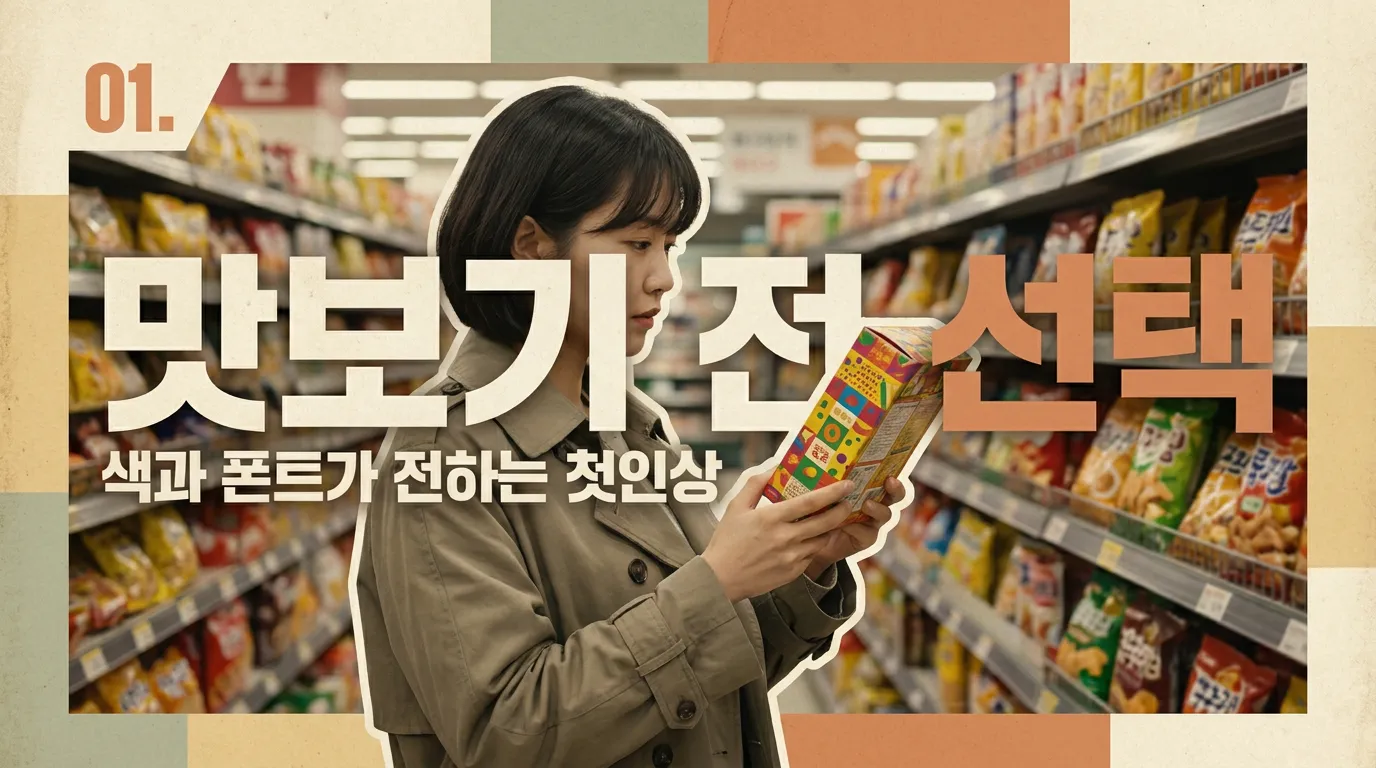
식품 브랜드 로고 디자인, 먹기 전 장바구니에 넣게 되는 색·폰트 5가지
식품 포장에서 소비자가 맛을 예상하게 만드는 로고 색상, 채도, 폰트, 여백, 원재료 표현 기준을 실무 관점으로 짚었습니다.
마트 진열대 앞에서 소비자는 아직 한 입도 먹지 않았는데 이미 단맛, 산미, 고급스러움을 짐작합니다.
빨강을 쓰면 무조건 맛있어 보일까요?
아닙니다. 먼저 정할 건 색이 아니라 맛의 약속입니다. 달고 진한 디저트라면 따뜻한 계열이 유리하고, 샐러드·저당·곡물처럼 가벼운 제품은 차가운 계열이 더 자연스럽습니다.
Frontiers in Nutrition에 실린 식품 패키지 색 연구도 비슷한 결론을 냅니다. 맛있지만 건강 이미지는 약한 식품은 따뜻한 색, 건강하지만 맛 기대가 약한 식품은 차가운 색에서 구매 의도가 높아졌습니다. 그러니까 빨강이 정답이 아니라 제품 성격과 색이 맞아야 합니다. (frontiersin.org)
파스텔은 건강해 보이는데 왜 밍밍해질까요?
파스텔은 깨끗하고 순해 보입니다. 문제는 맛의 농도까지 낮아 보일 수 있다는 점입니다. 잼, 소스, 스낵처럼 한 숟갈의 임팩트를 팔아야 하는 제품에 너무 흐린 색을 쓰면 소비자는 진하기보다 순한 맛을 먼저 떠올립니다.
ScienceDirect의 패키지 색 리뷰에서도 색은 매대에서 눈에 띄는 역할뿐 아니라 맛, 향, 브랜드 기대를 함께 만든다고 봅니다. 제가 현장에서 보면 대표님들이 가장 자주 놓치는 게 채도입니다. 색상보다 진하기가 먼저 맛을 말할 때가 많습니다. (sciencedirect.com)
둥근 폰트와 각진 폰트, 맛이 달라 보일까요?
달라 보입니다. 둥근 글자는 부드럽고 달콤한 쪽으로 읽히고, 각진 글자는 산미·쌉쌀함·탄산감 쪽으로 읽히기 쉽습니다. 옥스퍼드 신경과학 자료에 소개된 서체와 맛 연구에서도 둥근 서체는 sweet, 각진 서체는 bitter·salty·sour와 더 연결됐습니다. (neuroscience.ox.ac.uk)
그래서 크림빵 로고에 칼날 같은 글자를 쓰거나, 매운 스낵에 너무 동글동글한 글자를 쓰면 맛 신호가 엇갈립니다. 예쁜 폰트보다 먼저 봐야 할 건 씹히는 식감과 첫맛입니다.
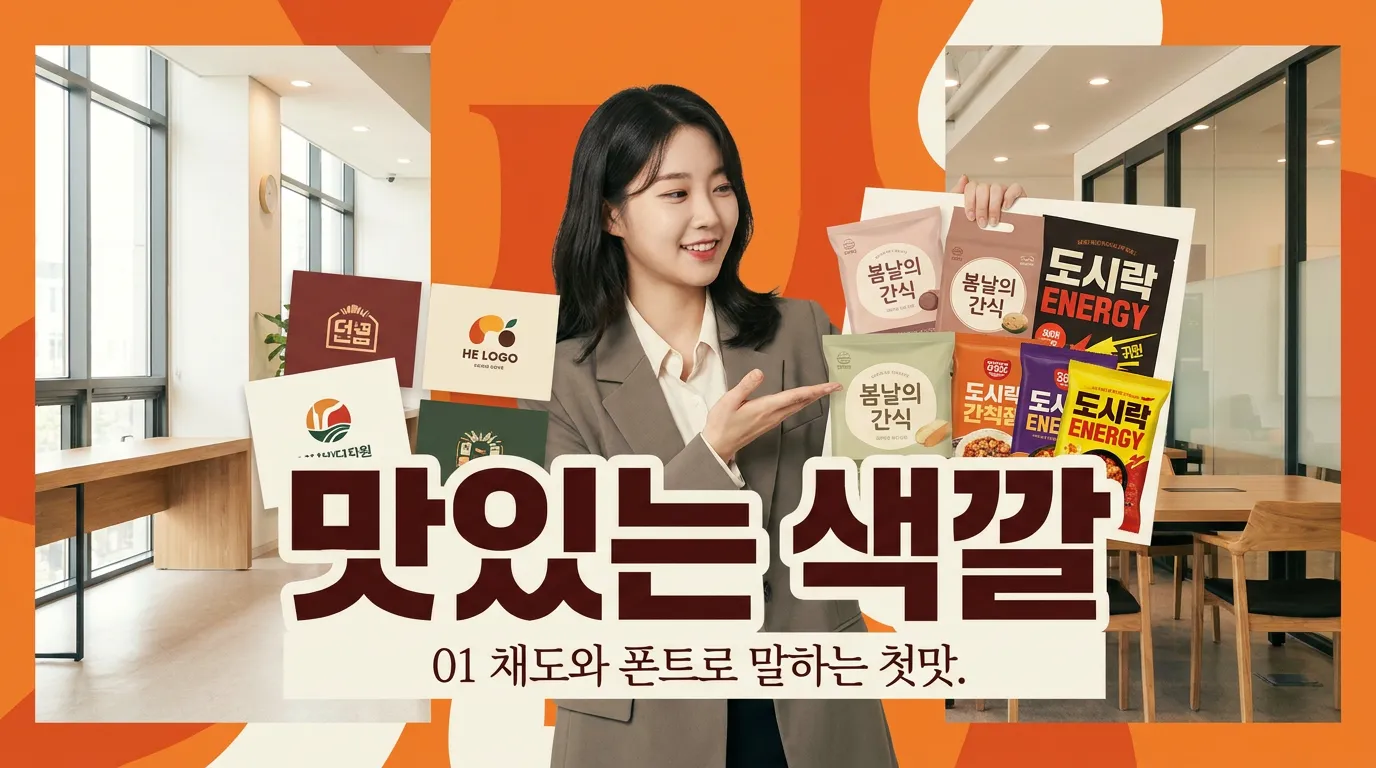
로고는 크게 넣을수록 잘 팔릴까요?
처음 나온 제품은 크게, 이미 설명할 재료가 많은 제품은 작게 가는 편이 낫습니다. 식품안전나라 설명처럼 주표시면은 소비자가 보통 먼저 보는 면이고, 제품명과 내용량이 들어갑니다. 즉 로고는 법정 정보와 경쟁하는 자리에 놓입니다. (foodsafetykorea.go.kr)
마크에서 식품 브랜드 로고 디자인을 잡을 때도 포장 정면을 먼저 봅니다. 로고가 주인공인지, 맛 이름이 주인공인지, 원재료 컷이 주인공인지 하나만 정합니다. 셋 다 크게 외치면 소비자는 아무것도 못 듣습니다.
원재료 그림은 많이 넣을수록 설득될까요?
원재료는 많이 보여주는 게 아니라 정확히 보여줘야 합니다. 제품명에 원재료명이 들어가면 함량 표시 이슈가 생길 수 있고, 소비자를 오인하게 하는 표현도 피해야 합니다. 국가법령정보센터의 식품등의 표시기준도 이 부분을 다룹니다. (law.go.kr)
그래서 딸기 3알 사진보다 딸기향 제품인지, 딸기 함량이 말할 만한 수준인지가 먼저입니다. 로고·색·폰트가 만든 기대를 실제 내용물이 못 따라오면 첫 구매는 가능해도 재구매에서 무너집니다.